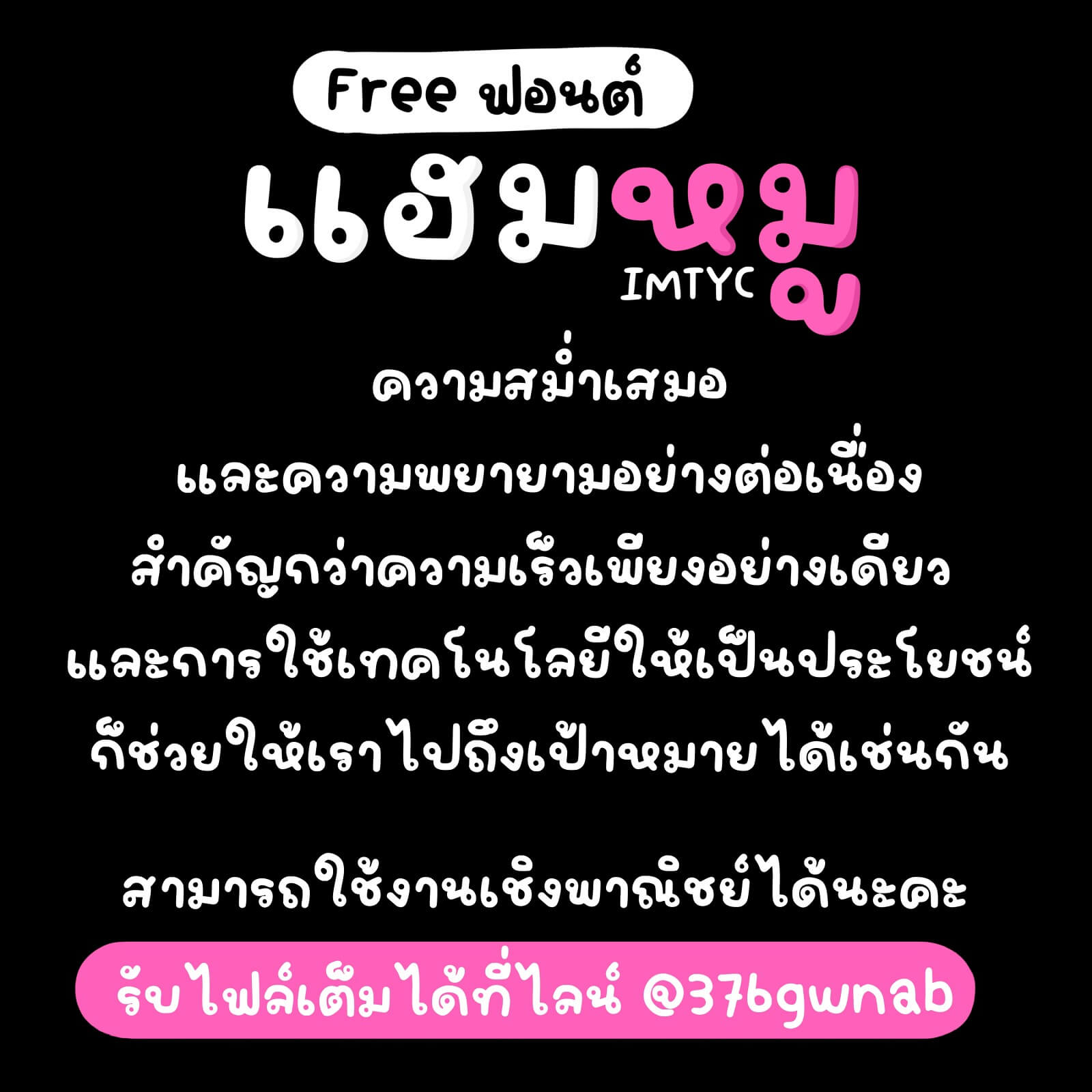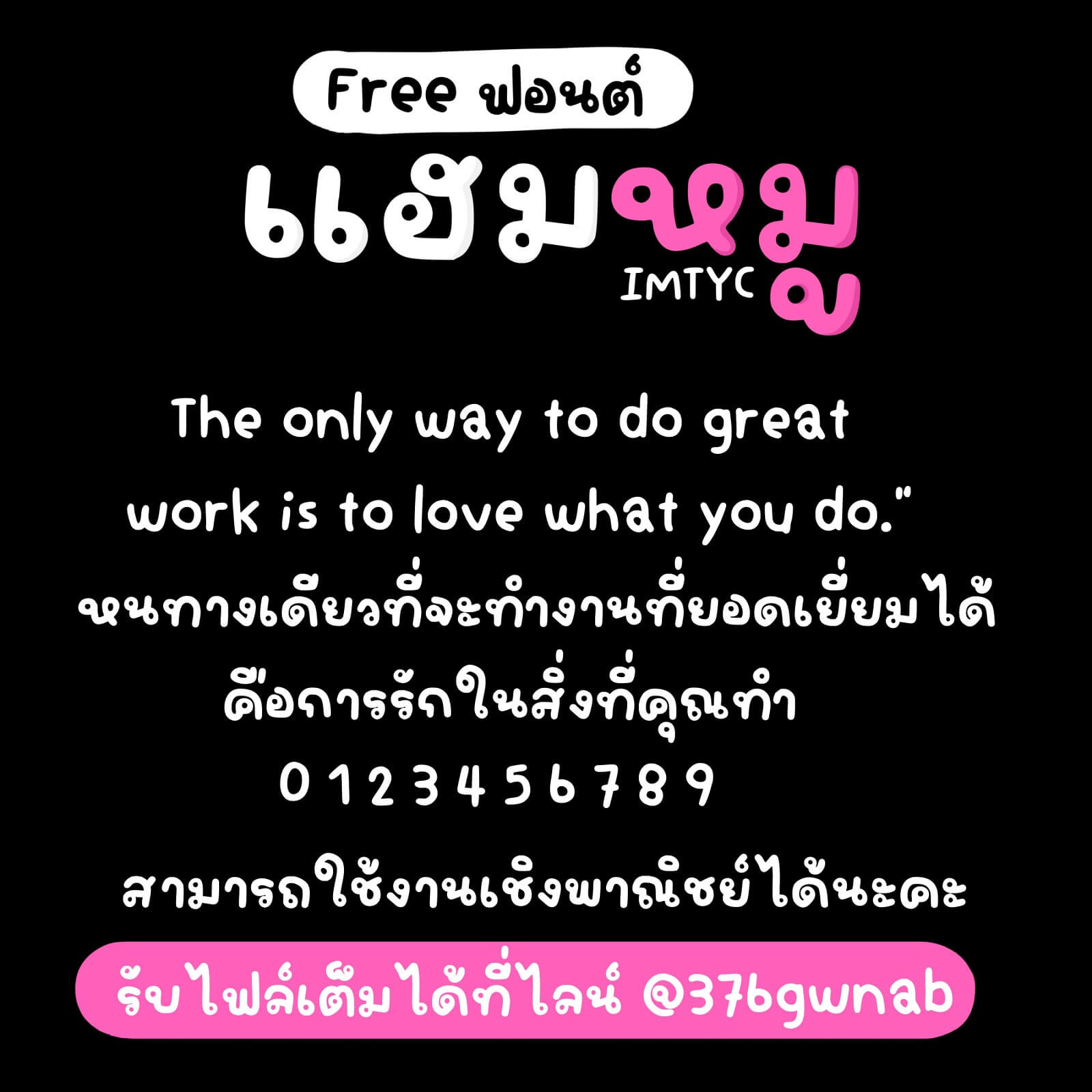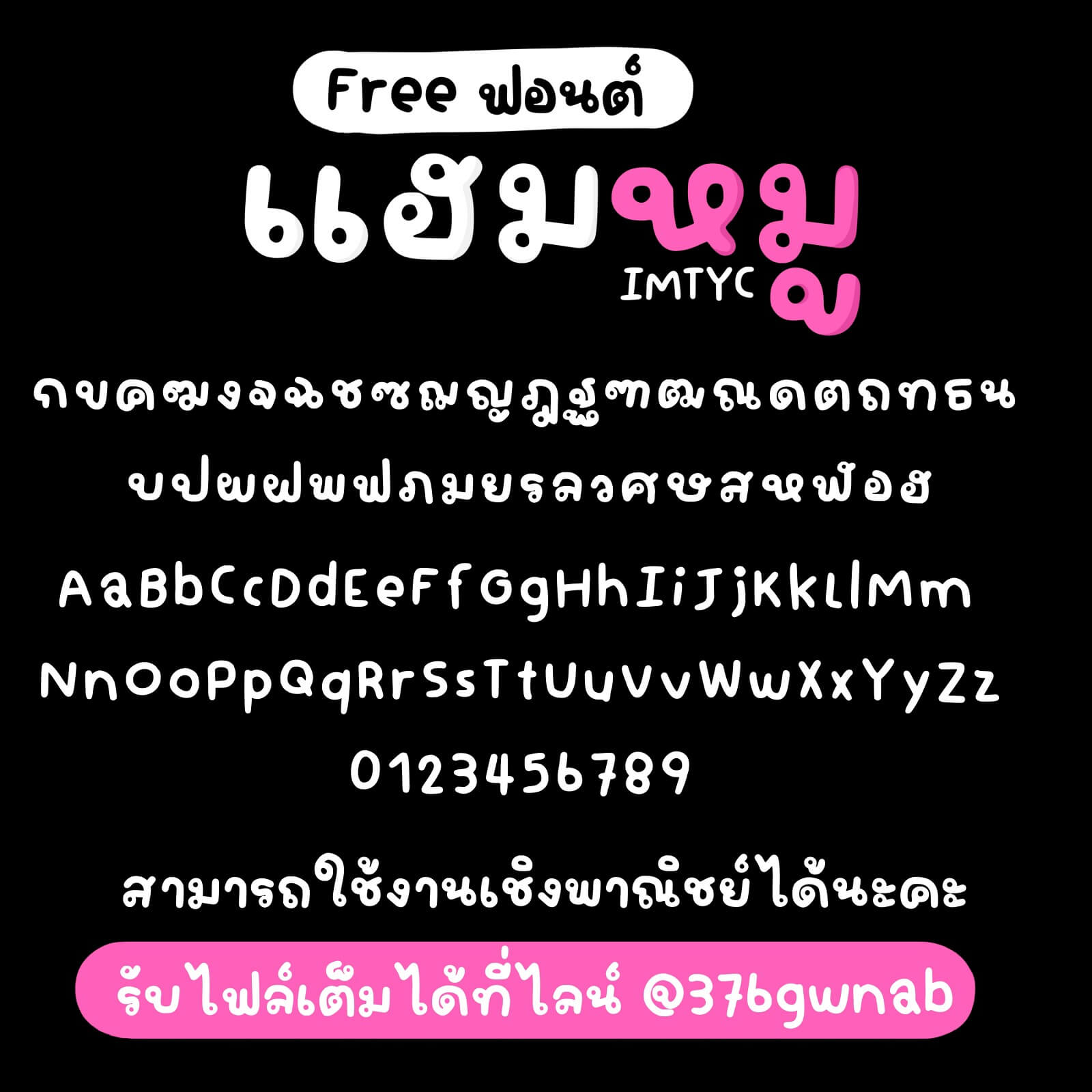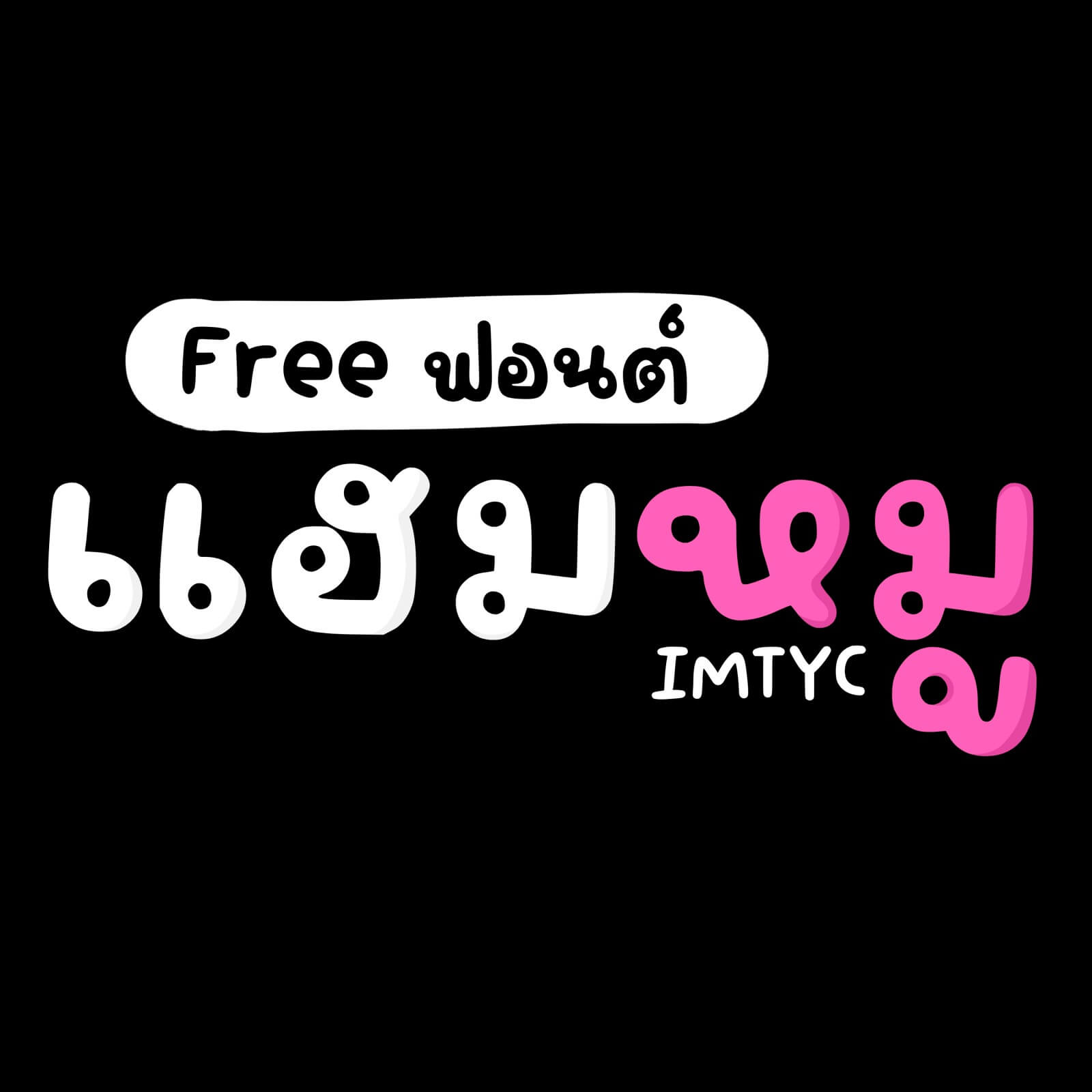
แฮมหมู (IMTYC Haemmoo)
แจกฟรี !! ✨ IMTYC Haemmoo –ฟอนต์แฮมหมู ตัวกลมอ้วน ขีดนุ่มแบบบรัช
ฟอนต์นุ่มนิ่ม เส้นกลมกลางหนา อ่านง่าย ใช้แล้วอบอุ่นใจ
เหมาะกับทุกสายครีเอเตอร์ ไม่ว่าจะใช้ทำป้าย ข้อความ โพสต์ หรือคอนเทนต์น่ารัก